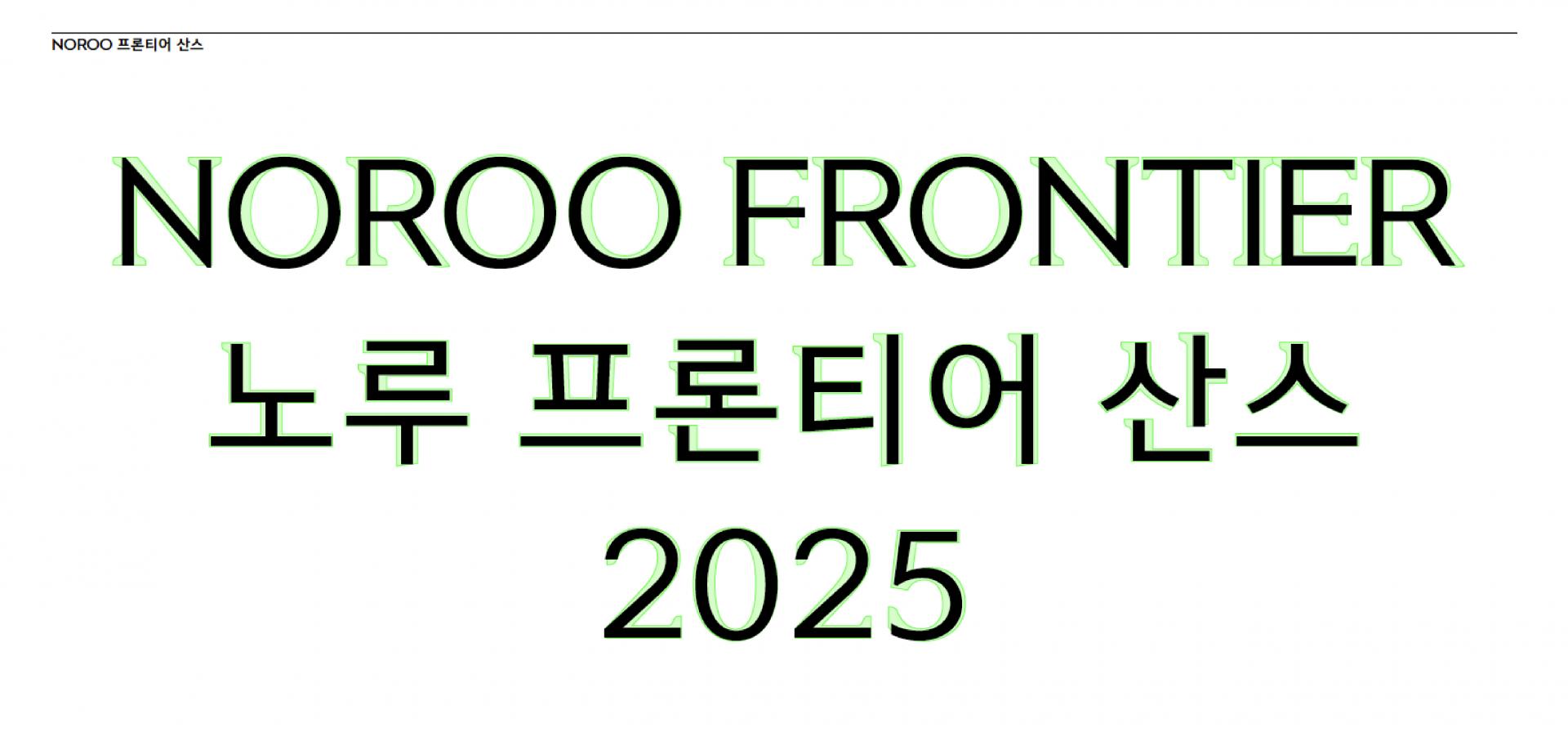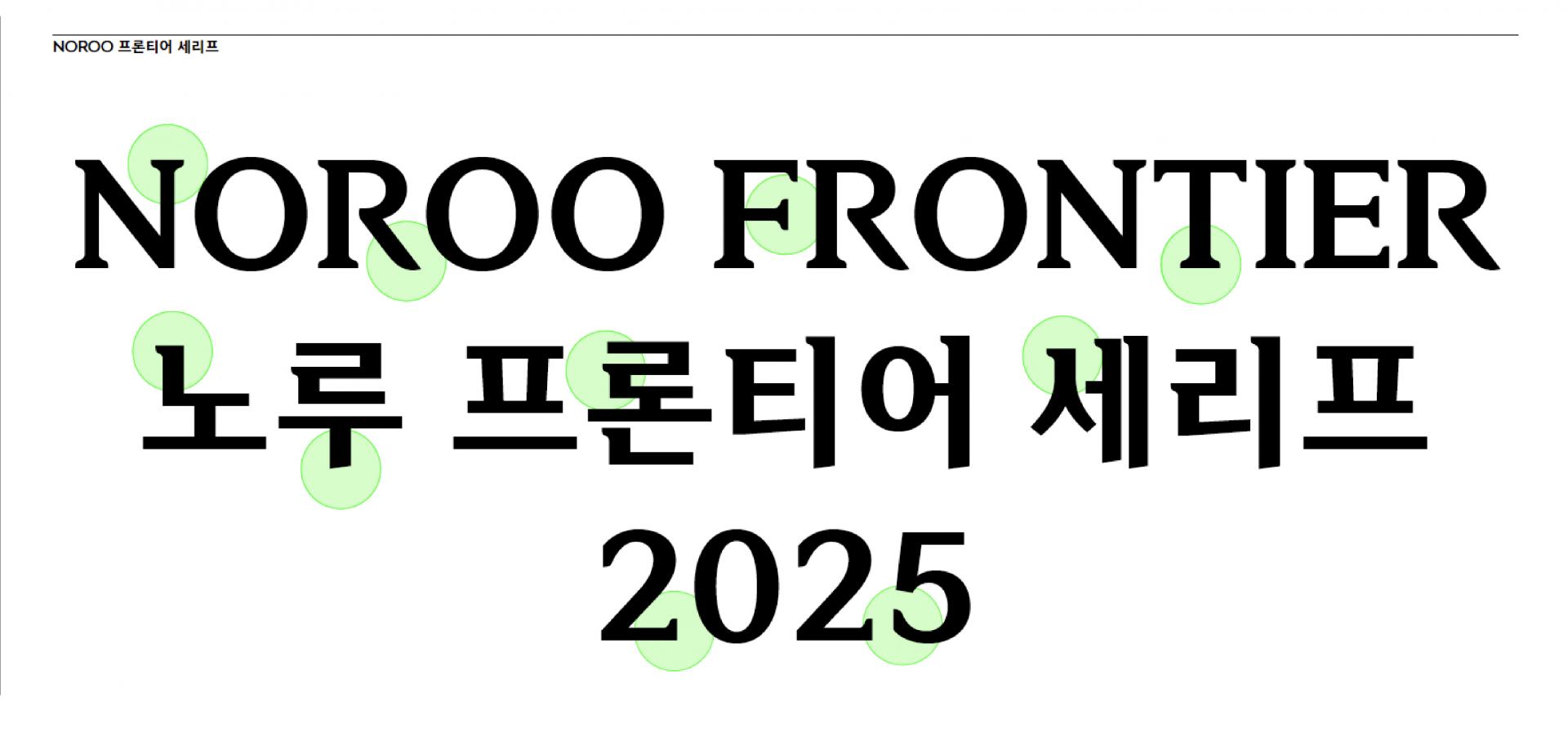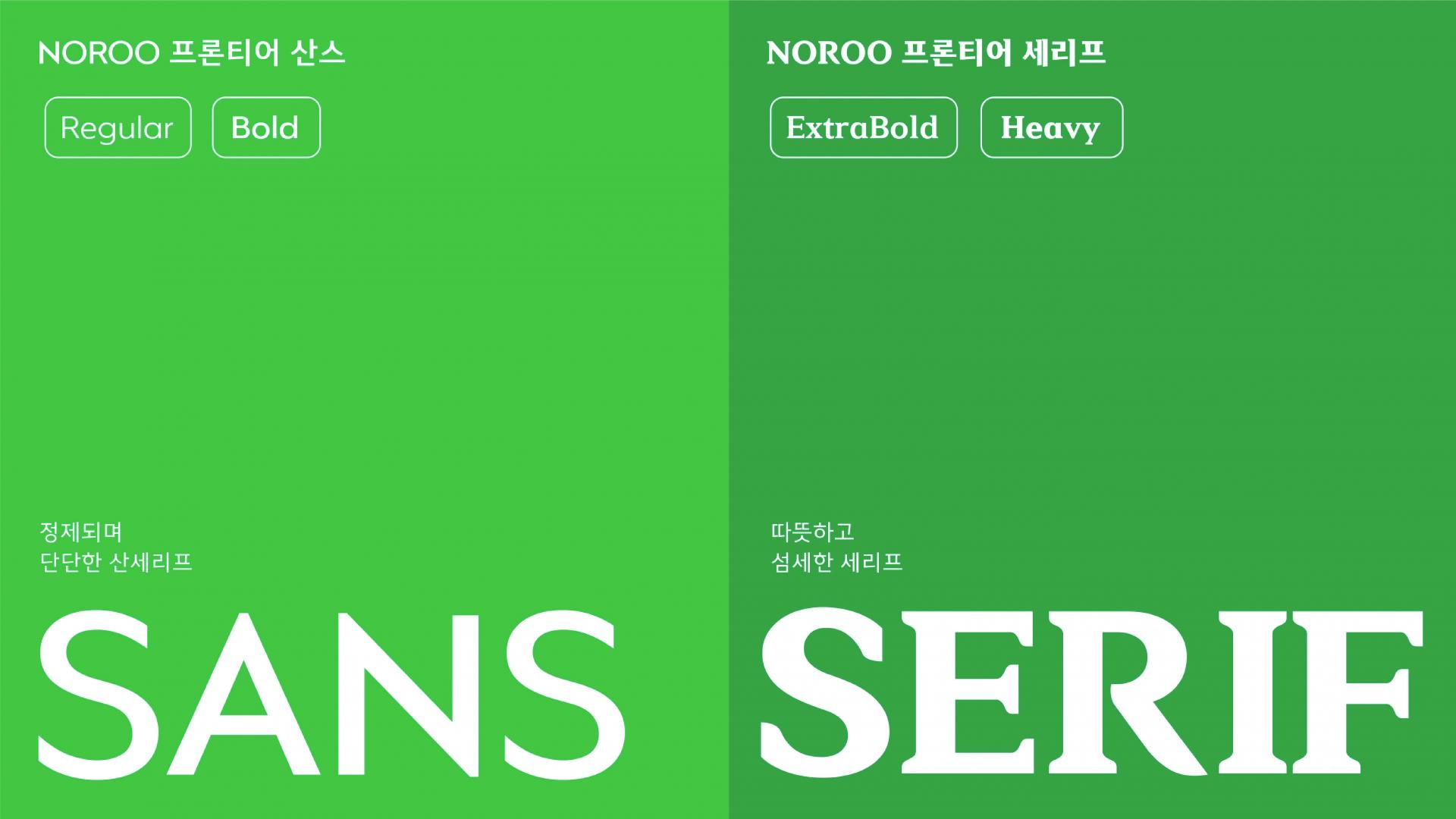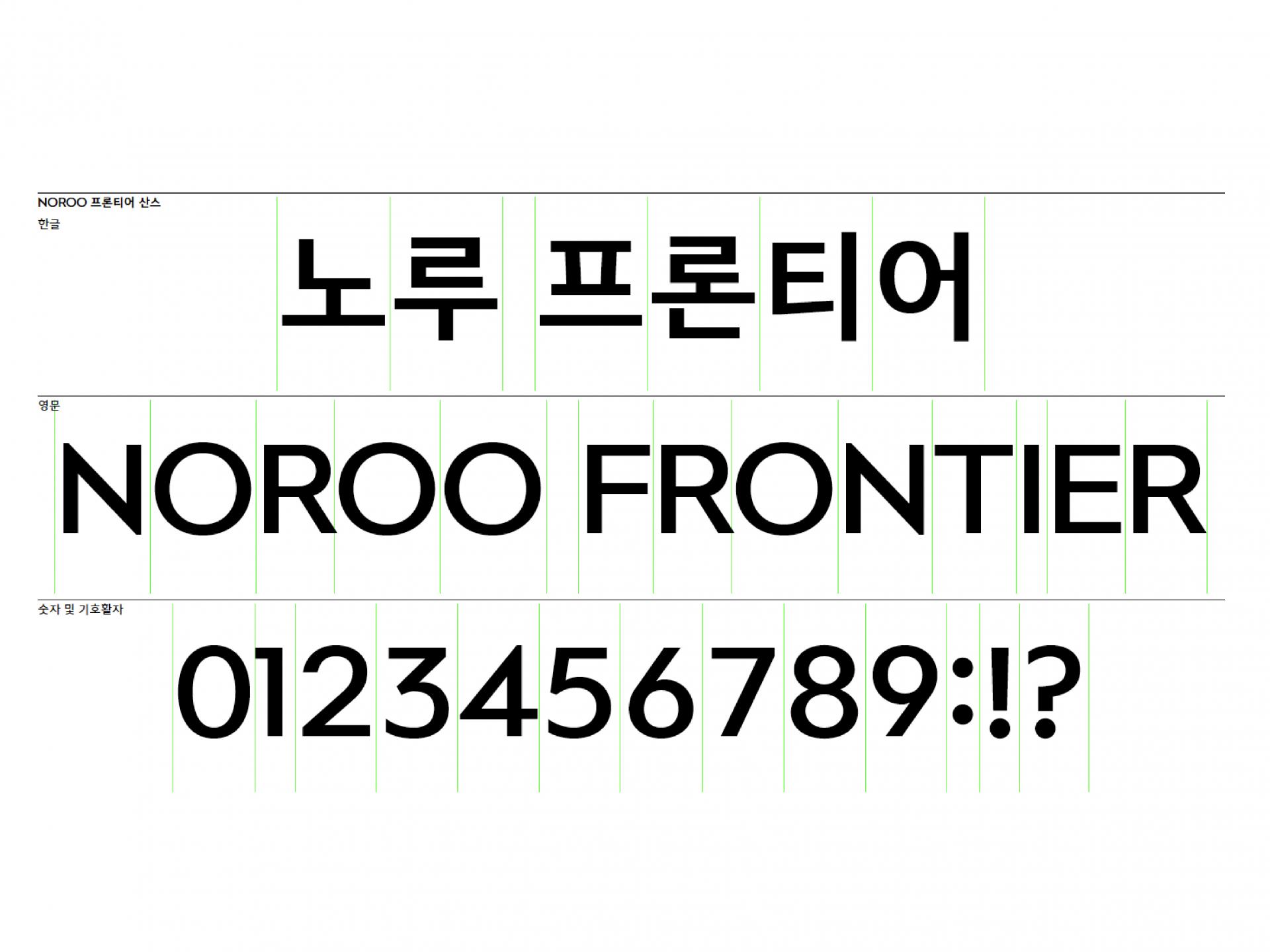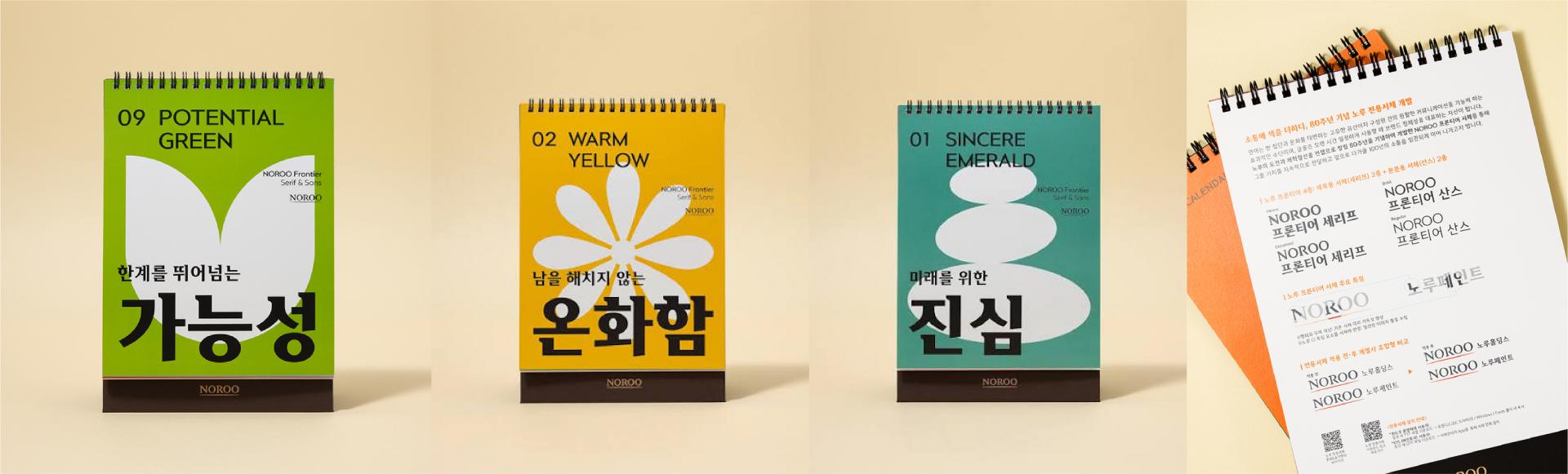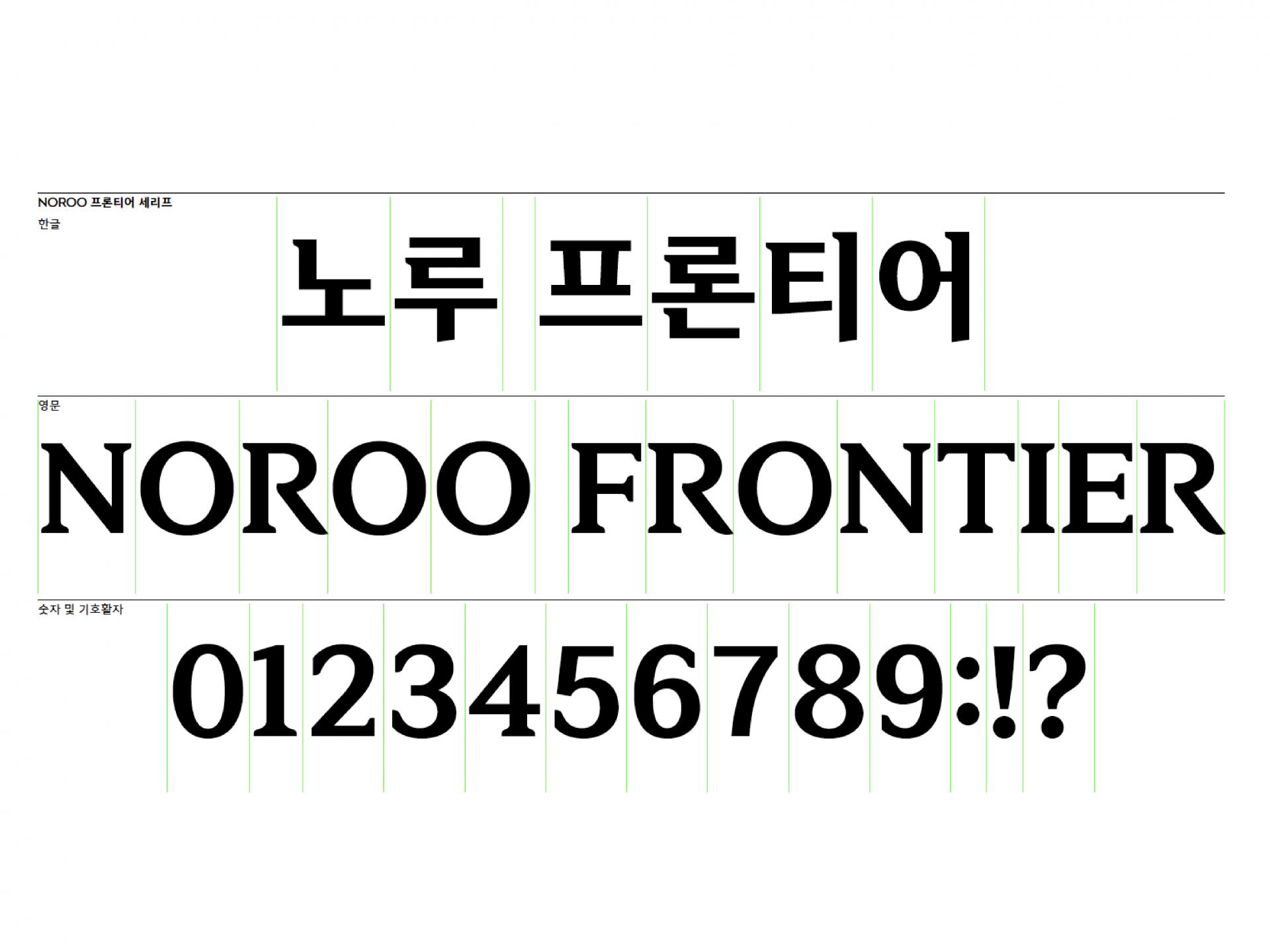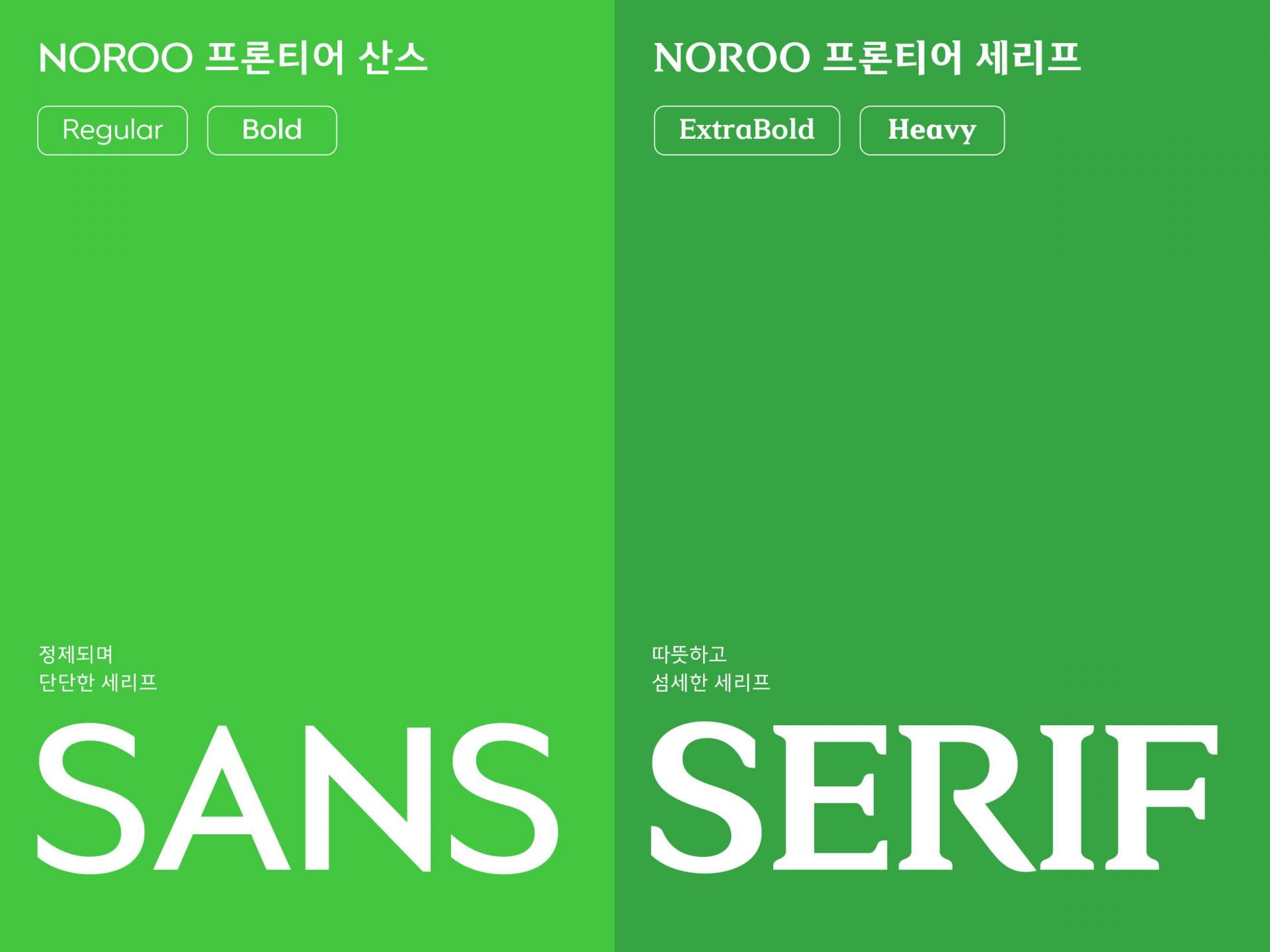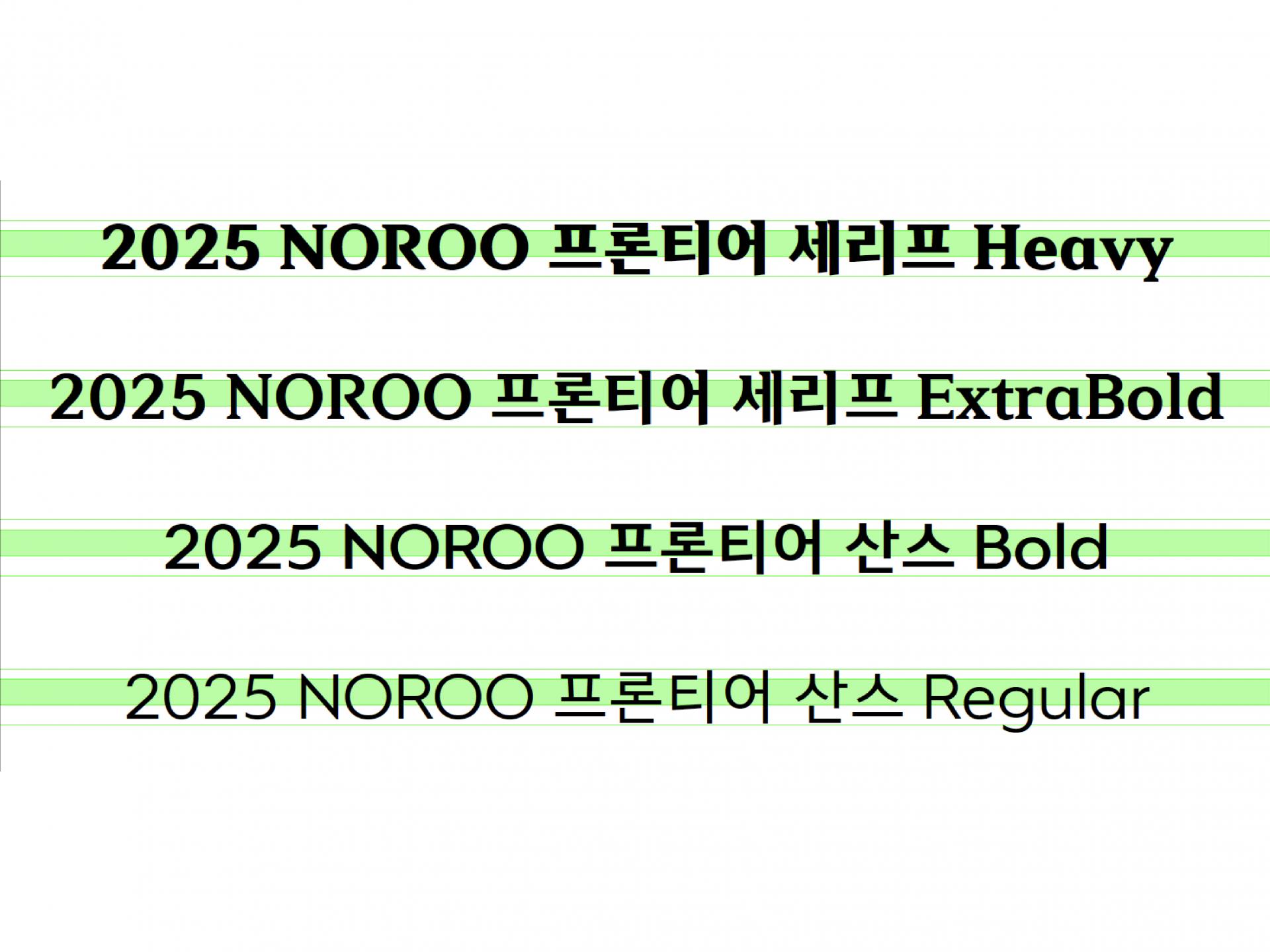
노루홀딩스 [프론티어산스, 프론티어세리프]
NOROO 프론티어는 노루의 80년 역사를 현대적으로 표현한 제목용 서체입니다. 장체 비례와 단단한 슬랩세리프로 세련되고 힘 있는 인상을 구현한 세리프와, 동일한 뼈대를 바탕으로 큼직한 닿자와 정원에 가까운 ‘ㅇ’꼴을 적용해 밝고 선명한 인상을 완성한 산스로 구성됩니다. 두 서체는 일관된 브랜드 DNA를 공유하며, 다양한 광고 환경에서도 높은 시인성과 주목도를 제공합니다.